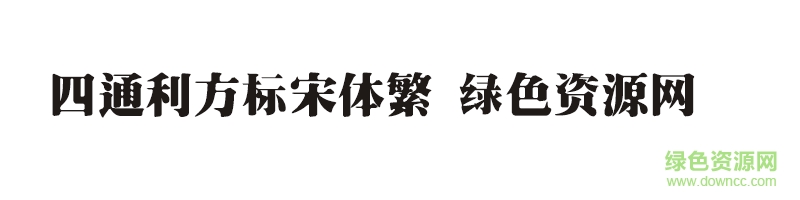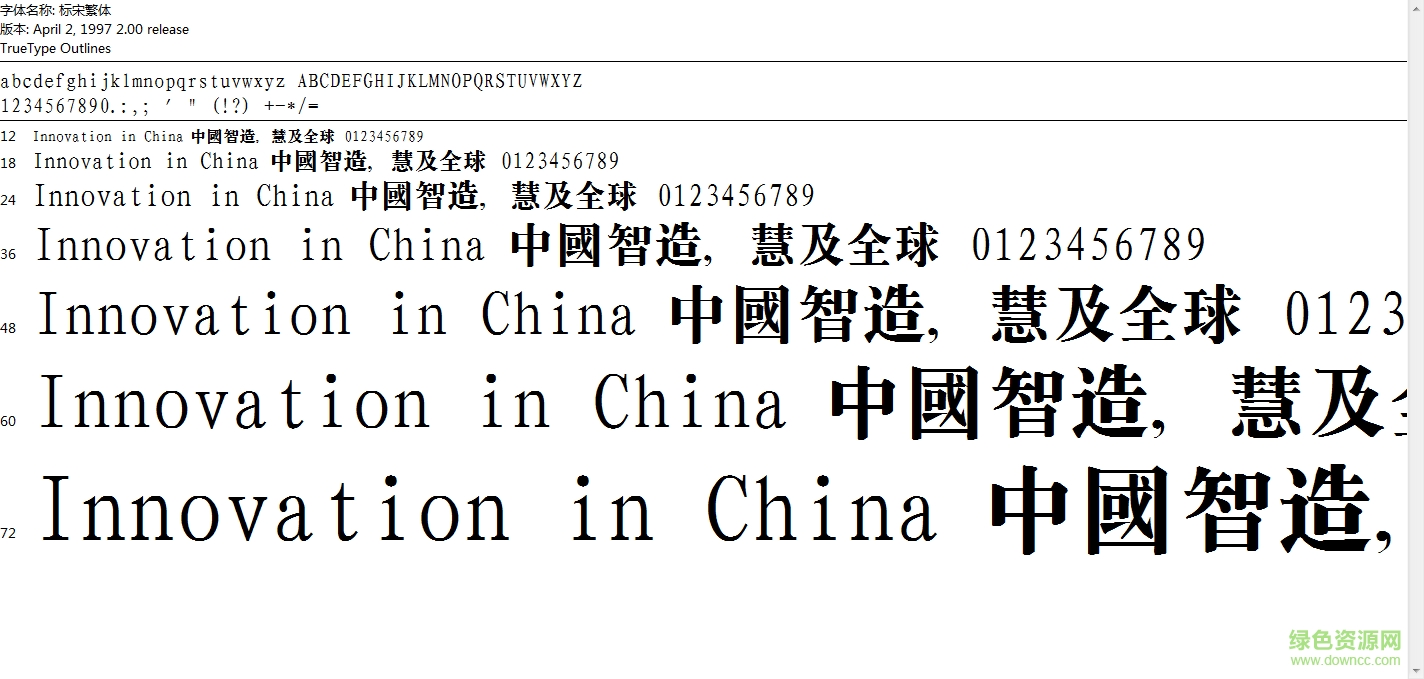
四通利方標(biāo)宋體繁是一款非常好看的繁體字體,字體粗細(xì)均勻,外形美觀(guān),支持漢子、阿拉伯?dāng)?shù)字、英文三大文字,應(yīng)用范圍非常廣泛,歡迎下載來(lái)綠色資源網(wǎng)使用!
四通利方標(biāo)宋體繁字體是保留了四通利方原版的優(yōu)雅以及高可讀性的特色,并在四通利方的基礎(chǔ)上做出了變化,使得整套字體看起來(lái)更加銳利清晰。